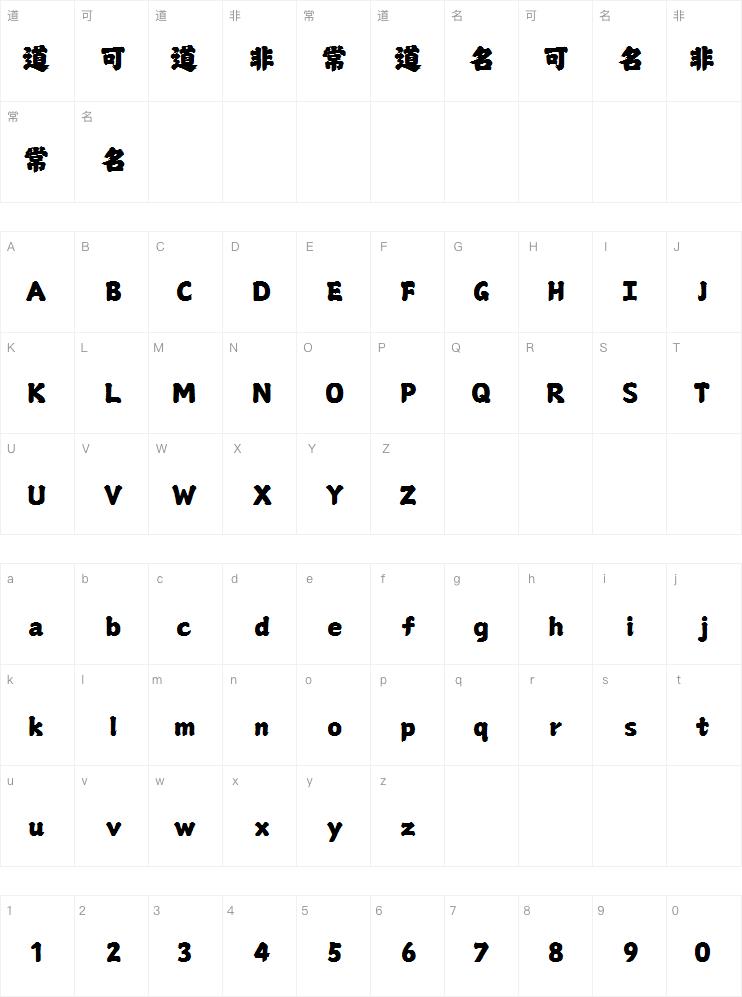
山海华夏榜书,是一款全新的字体,包含简繁汉字9169个,符号200+个,是一款大字榜书字体。该字体雄健有力,非常醒目!有力、宽厚、方正,如同巍峨的大山,充满了稳重感和设计感。古朴浑厚,笔画与字形间透露着榜书的古雅和刚劲的特点,在浑厚的同时而又极富张力,桀骜不驯的特性,霸气外露。它的笔画充满力量感,组合搭配极富强烈的节奏感。在粗细的纵横间,拥有非常规的张力特性。